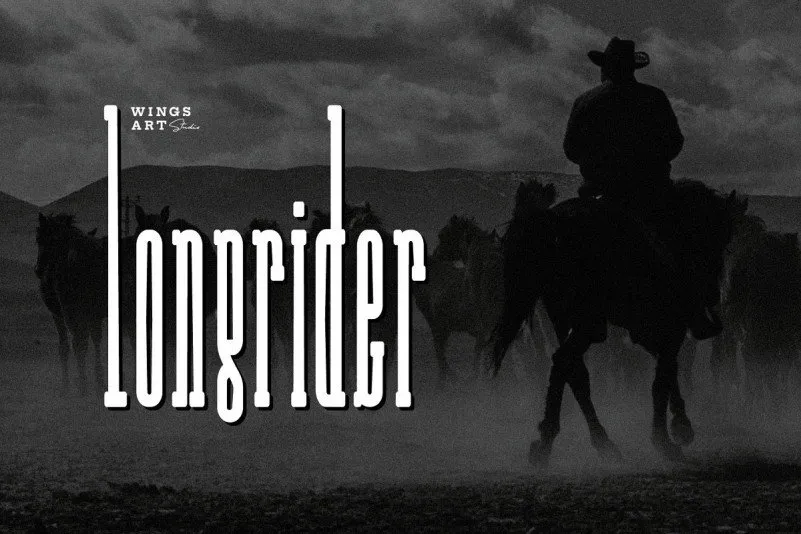
Long Rider Slab Serif Font
A Long Rider Slab Serif Font é uma elegante serifada slab capaz de enriquecer seu design com estilo cowboy nostálgico. Inspirada no traço robusto e forte dos cowboys, esta fonte está pronta para dar vida a títulos, logotipos e layouts sociais de mídia. Seu formato é particularmente apropriado para designs em pé dura, proporcionando um texto deslumbrante que se adequa perfeitamente à tela das histórias do Instagram ou aos ambientes de produção widescreen grandiosos. Esta fonte combina elegância e robustez, permitindo-lhe explorar novas maneiras de expressar suas ideias no design gráfico, seja para títulos poderosos em portfólios de trabalho ou para personalizar sua presença digital com riqueza e estilo.